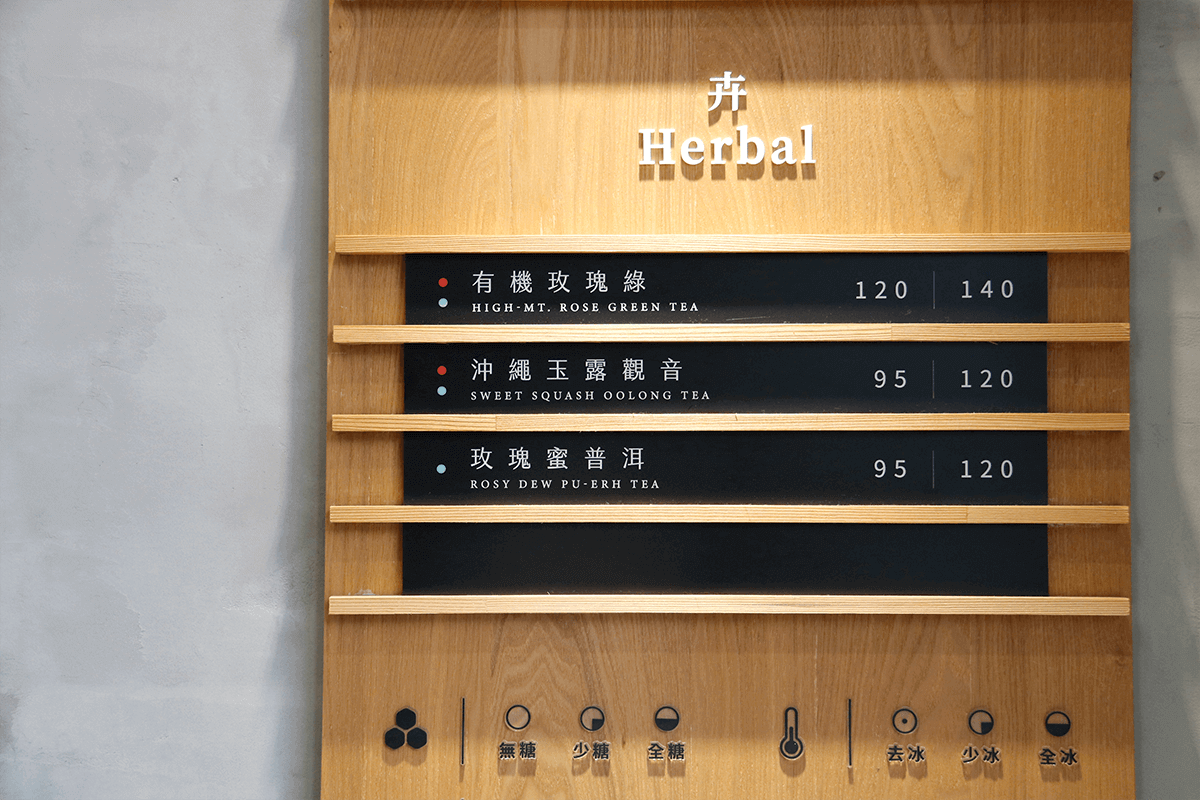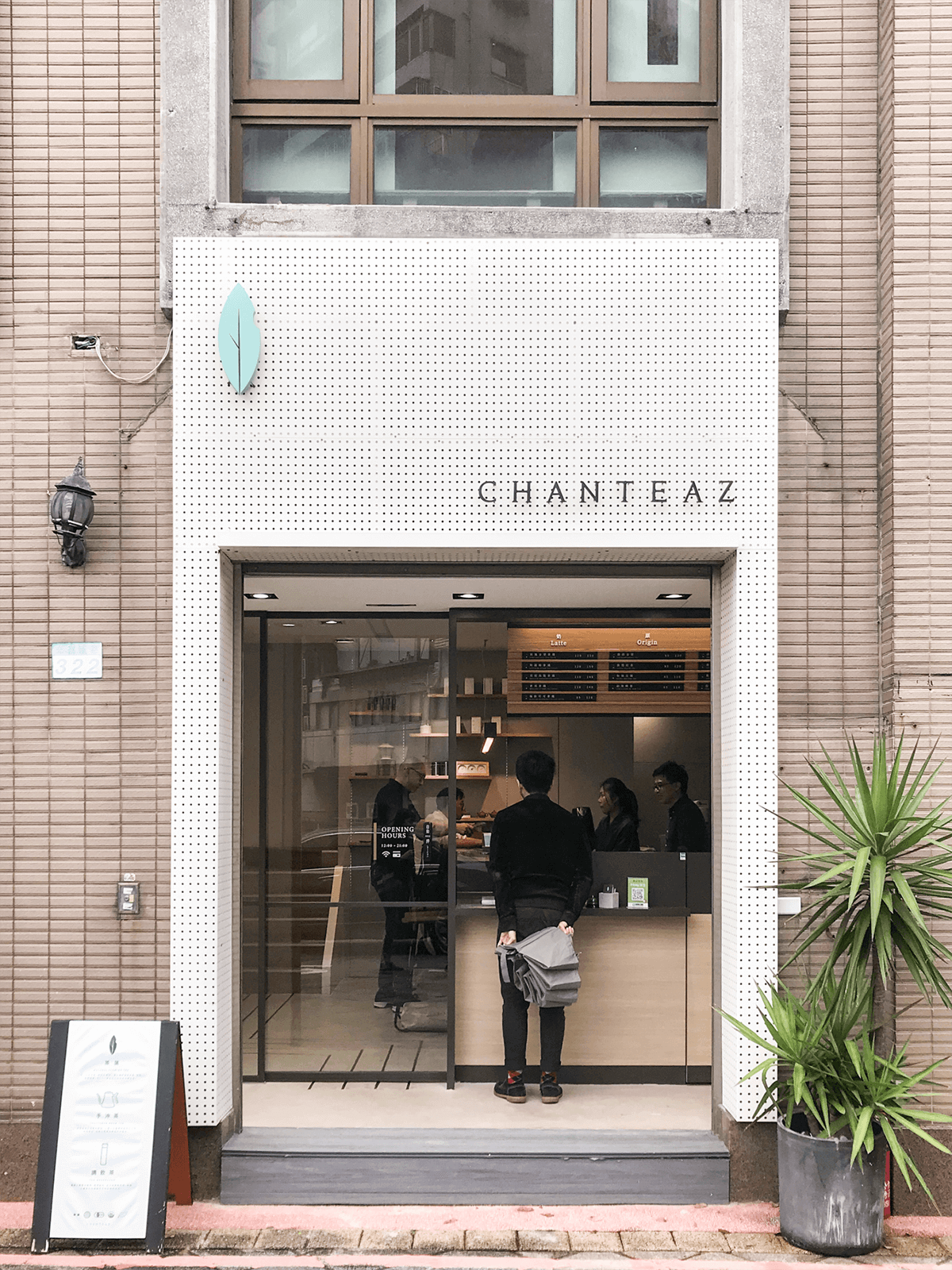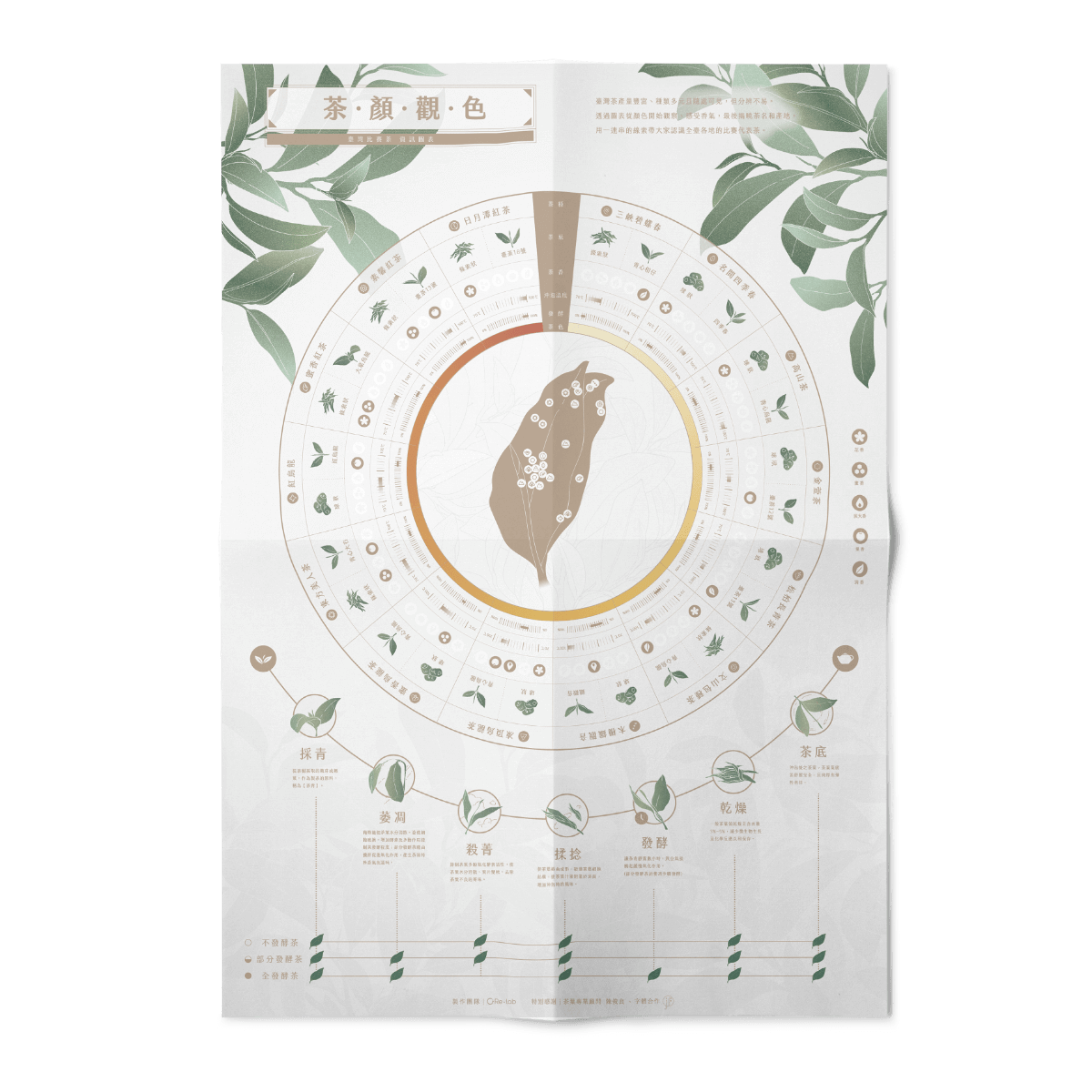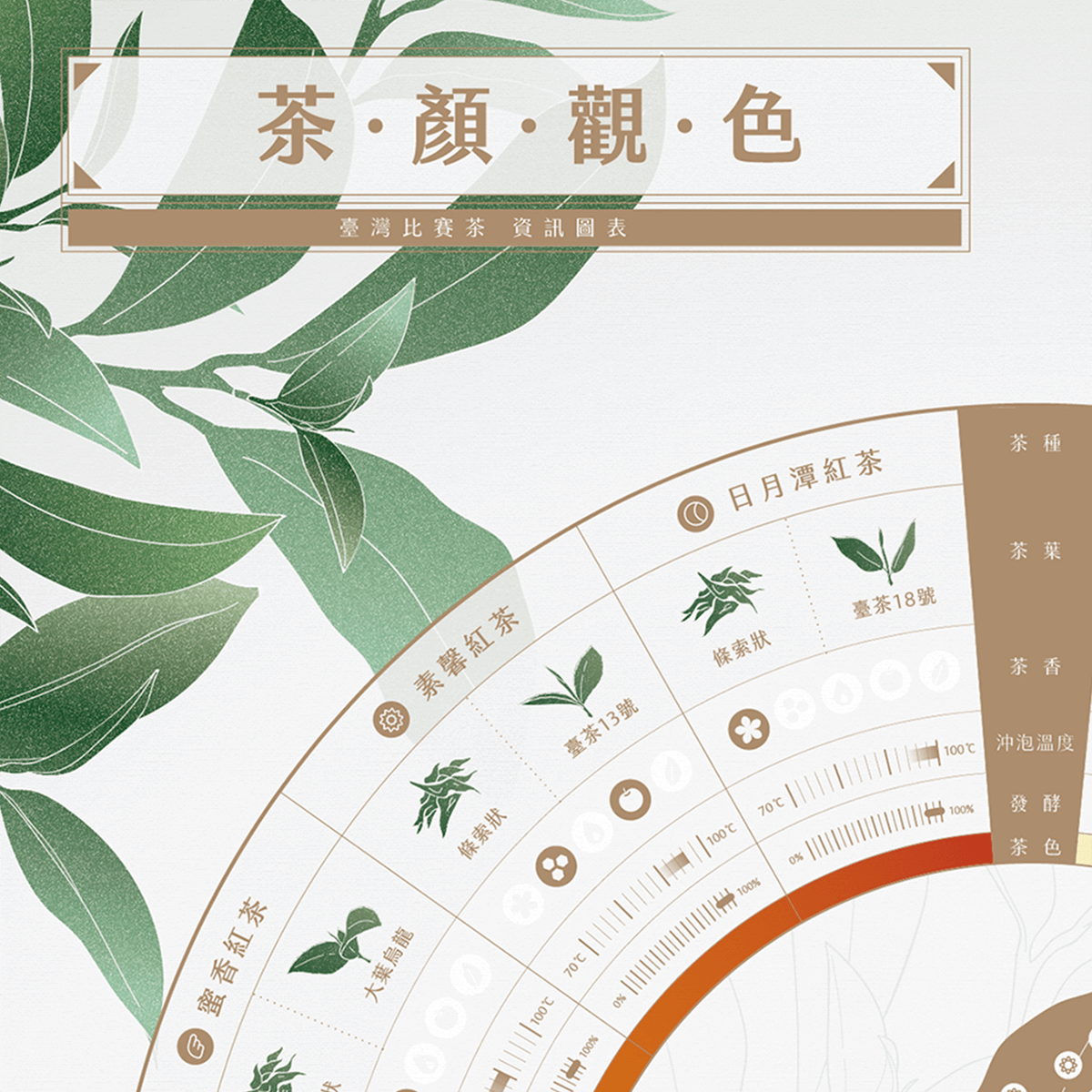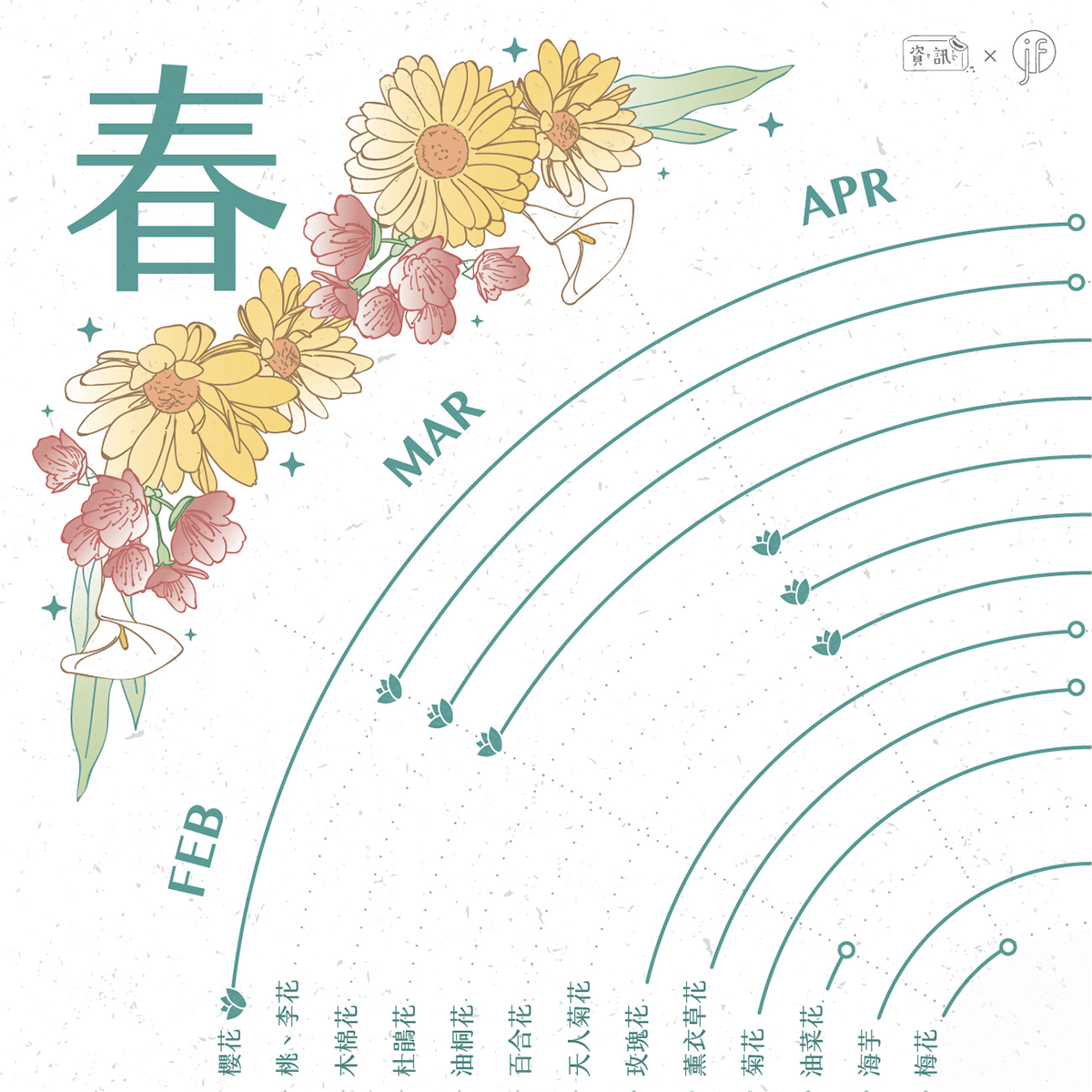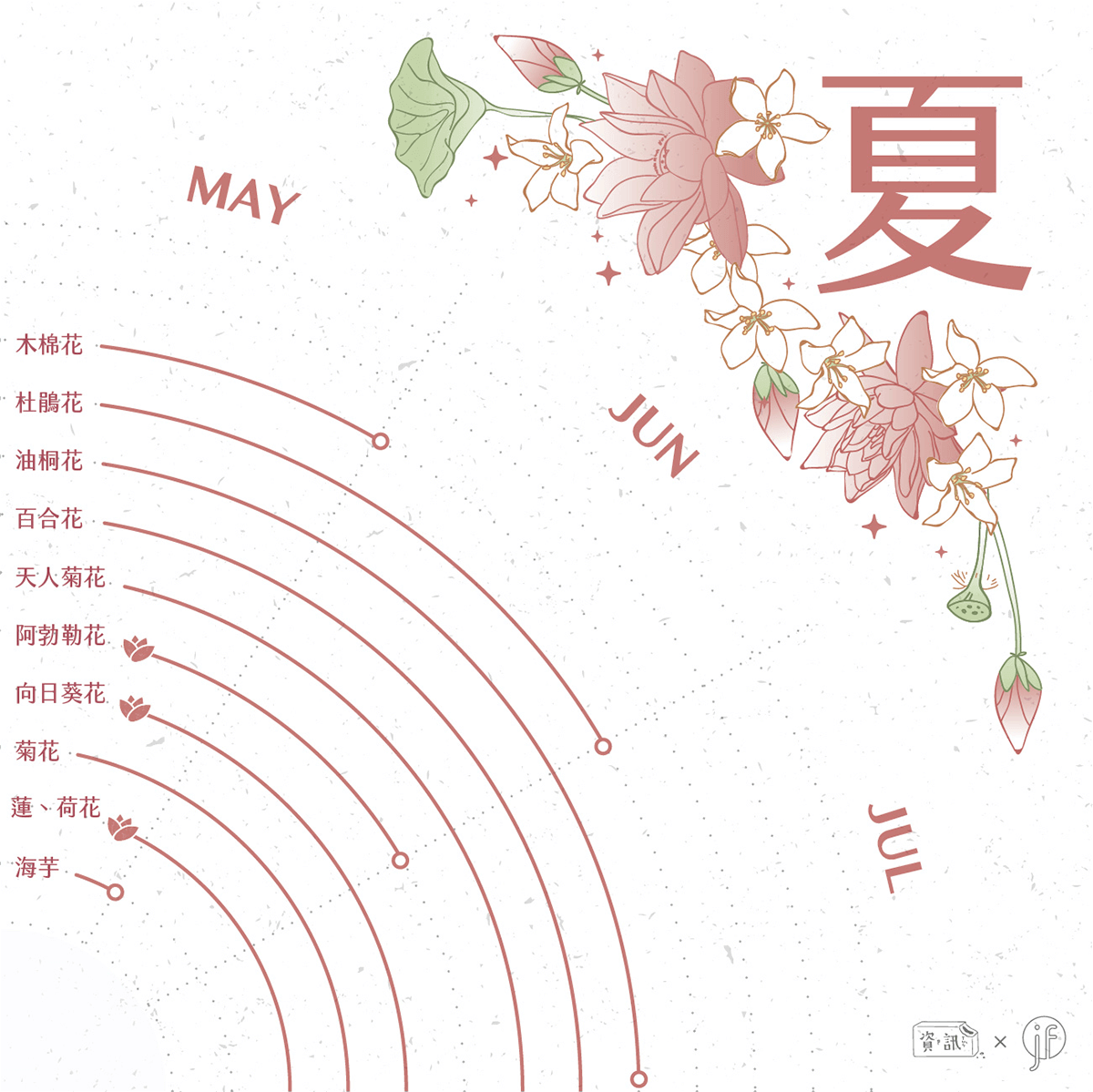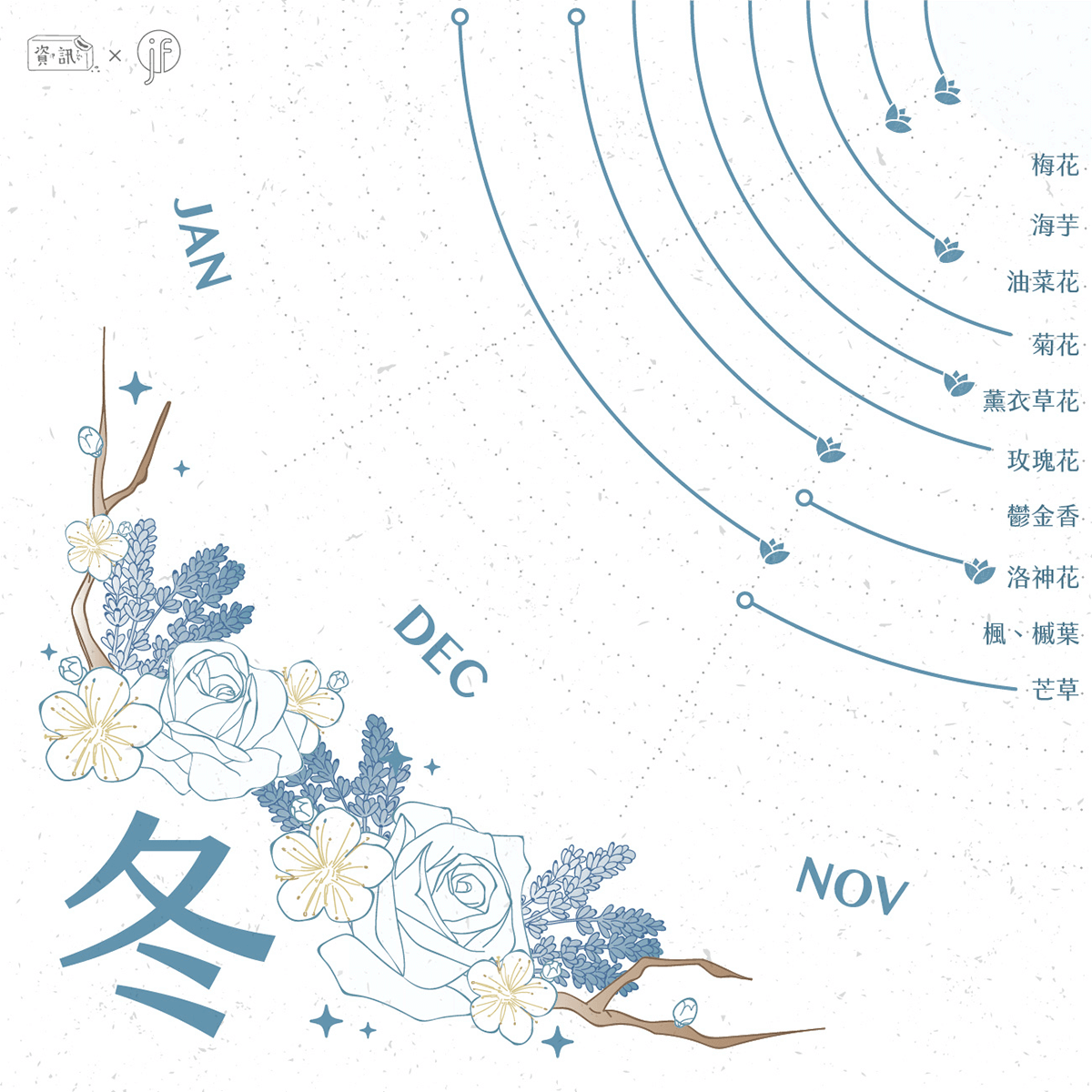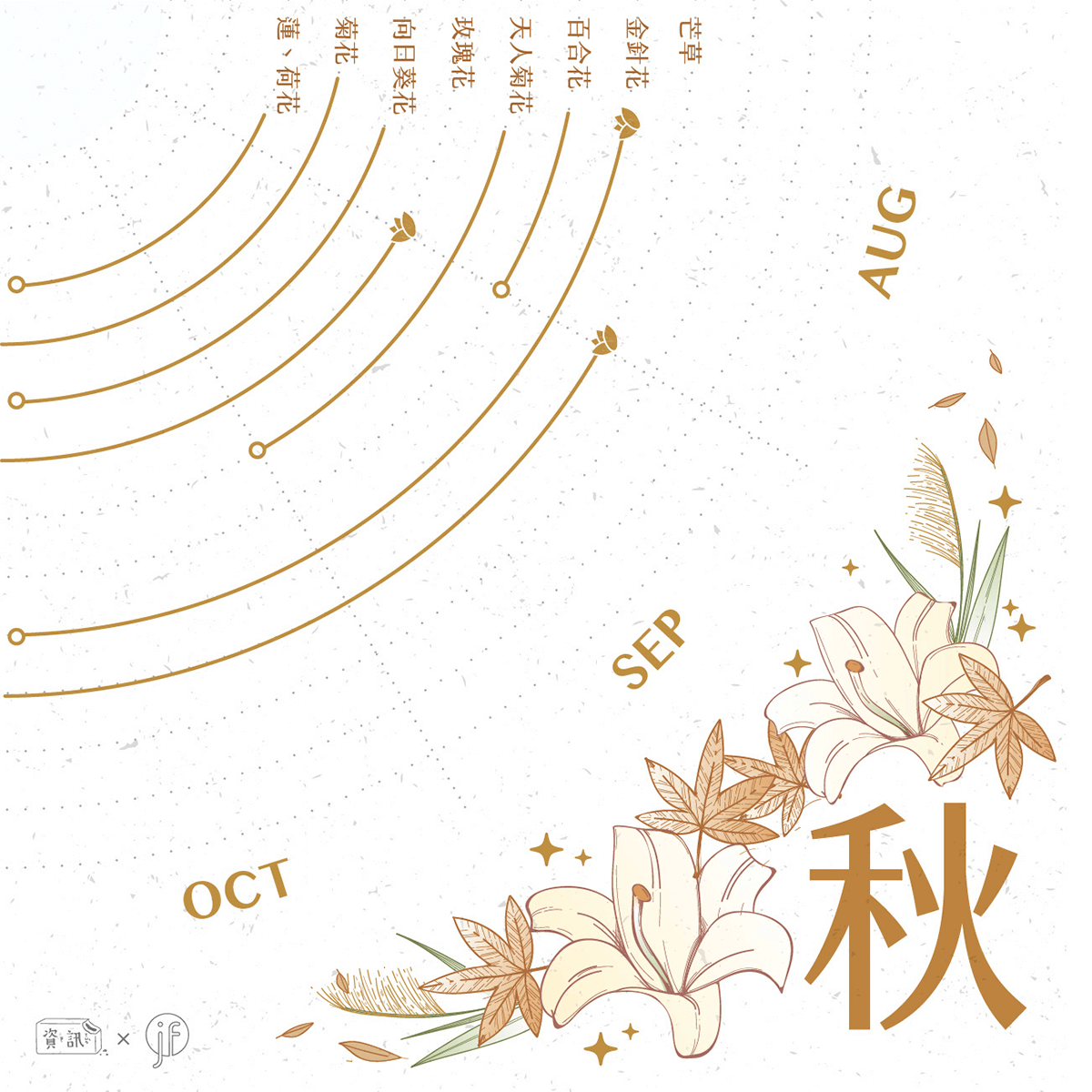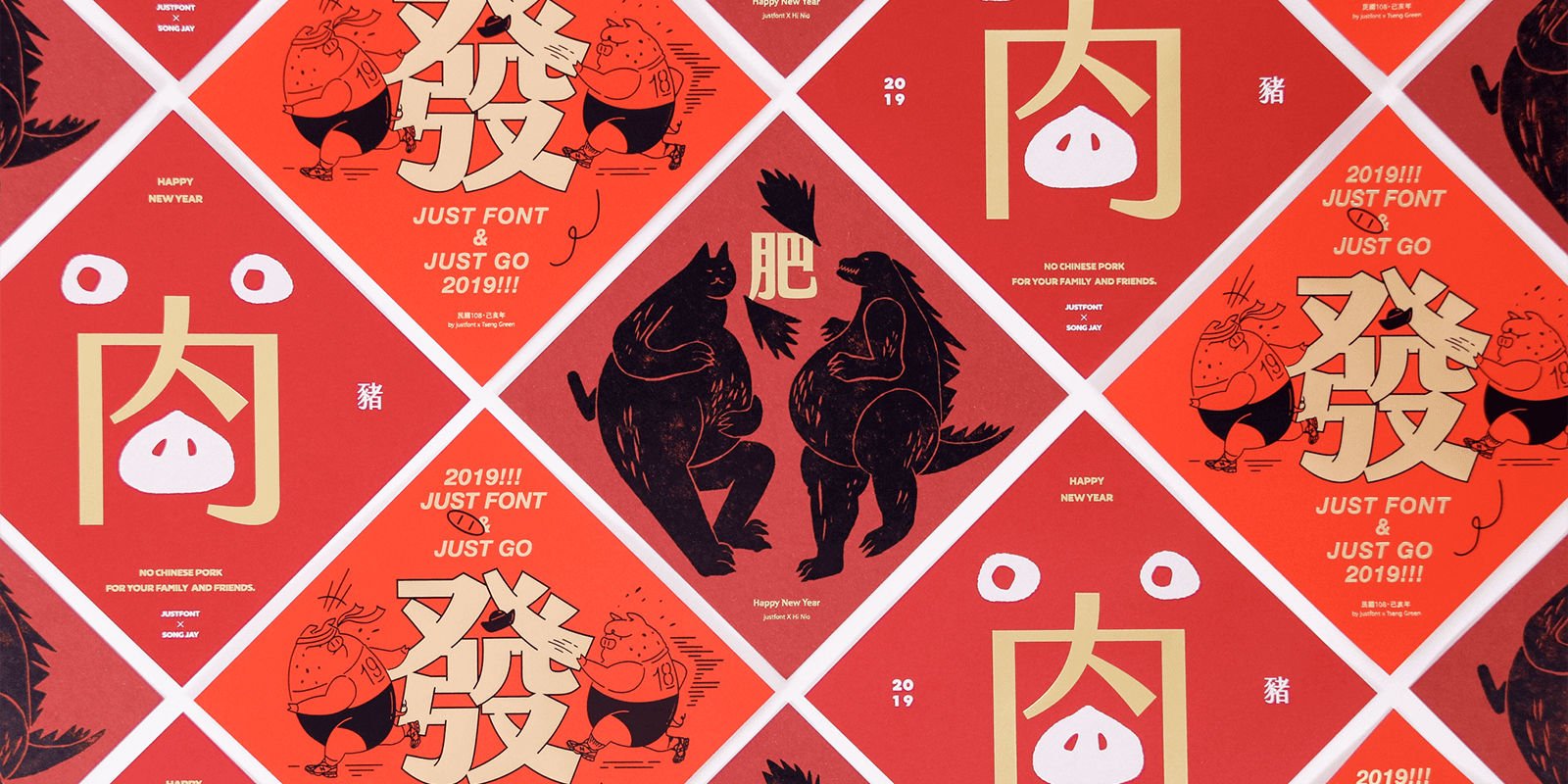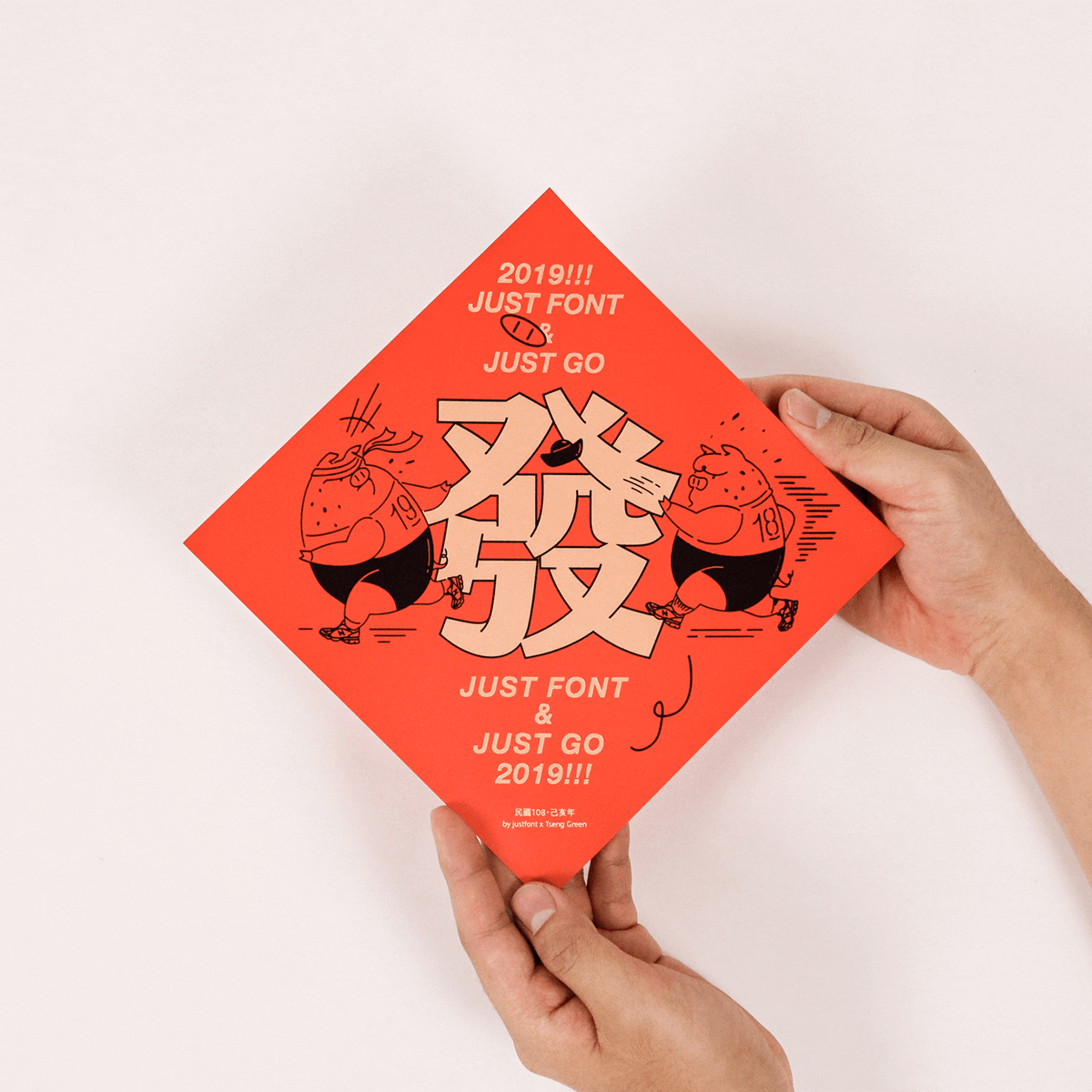
金萱
搭配應用
各種優異應用範例參考,滿足你的想像
精選應用
字型設計師盡全力追求一致而清晰的文字設計。但讓文字的美發揚光大,取決於我們如何使用字型。這些精選範例,都是 justfont 團隊深受啟發的應用。這些優秀的品牌、團隊,讓字型設計師知道自己的作品能帶來深刻的改變。也為我們示範了:即便不特別標榜優美、清新、溫柔、雅緻,只要用對字體,就能傳遞言語所無法塑造的感受。
資訊設計 justfont X Re-lab
由 Re-lab 資訊改造實驗室製作,用「茶顏觀色」一張圖解說台灣茶的各種面貌。另外,在「花季曆」也以視覺化手法讓不易快速理解吸收的資訊,變得一看就懂!除了欣賞美麗的圖像以外,有注意到文字的細節嗎?從大標題、重點小標到內文,都應用不同粗細的金萱字型。不只讓資訊設計最重要的「層級」更明確,還透出了清新優雅的氣息,讓這份作品不只訴說資訊,更具氣質與情感。
品牌設計 justfont X 賦茶
從小愛喝茶的賦茶 Chantez 品牌總監 Ian 與團隊一同打造了讓人們靜靜品味茶的美好空間。他們不只賣茶,更以顛覆傳統的方法,重新詮釋茶的精緻文化。金萱字型同時兼有明體的人文情感,還有黑體的現代簡潔,最適合展現賦茶的品牌精神。賦茶對價值的專注、對理念的堅持,更深獲 justfont 團隊的認同與共鳴。
春聯斗方
justfont X 時分印刷 X 設計師
設計師:曾國展
主題:發
「發」字除了象徵發財之外,同時加入了出發的概念,
把 2018 年自己沒完成的目標與理想,交棒給 2019 年的自己去努力,
再接再厲、財富永續,一起豬發吧!
字型使用由 justfont 所設計的金萱九分糖,
渾厚醒目的筆畫粗度將「飽滿」的概念襯托得更完整到位。
發
justfont X Tseng Green
「發」字除了象徵發財之外,同時加入了出發的概念,把 2018 年自己沒完成的目標與理想,交棒給 2019 年的自己去努力,再接再厲、財富永續,一起豬發吧 !
發:金萱九分糖
肥
justfont X Hi Nio
十二生肖裡面,怎麼可以缺少討喜的喵跟哥吉拉,一直讓他們閒著不見客都吃肥了,但這也是種幸福啦! 最後一輪的豬年,就讓他們陪大家一起肥肥的,萌萌的。
肥:金萱七分糖
設計師:倪嘉隆
主題:肥
十二生肖裡面,怎麼可以缺少討喜的喵跟哥吉拉,
一直讓他們閒著不見客都吃肥了,但這也是種幸福啦! 最後一輪的豬年,就讓他們陪大家一起肥肥的,萌萌的。
設計師:宋政傑
主題:肉
字體設計中當有了「骨」,便會開始長「肉」,長肉的過程中字體設計師會一筆一畫研磨,思考如何讓字更為精緻。
斗方以肉字結合肉包,上方的眼睛與肉包連結成一頭豬,肉字呼應字體設計師的偏執、一筆一畫的努力、堅持,肉包則期許自己能將好的精華不斷地精進,端出更好的佳餚。
標語為「No Chinese Pork for your family and friends」謹惕自己、家人,希望豬瘟 (壞運) 不要進來讓滷肉飯消失。
肉
justfont X Song Jay
字體設計中當有了「骨」,便會開始長「肉」,長肉的過程中字體設計師會一筆一畫研磨,思考如何讓字更為精緻。
斗方以肉字結合肉包,上方的眼睛與肉包連結成一頭豬,肉字呼應字體設計師的偏執、一筆一畫的努力、堅持,肉包則期許自己能將好的精華不斷地精進,端出更好的佳餚。標語為「No Chinese Pork for your family and friends」謹惕自己、家人,希望豬瘟 (壞運) 不要進來讓滷肉飯消失。